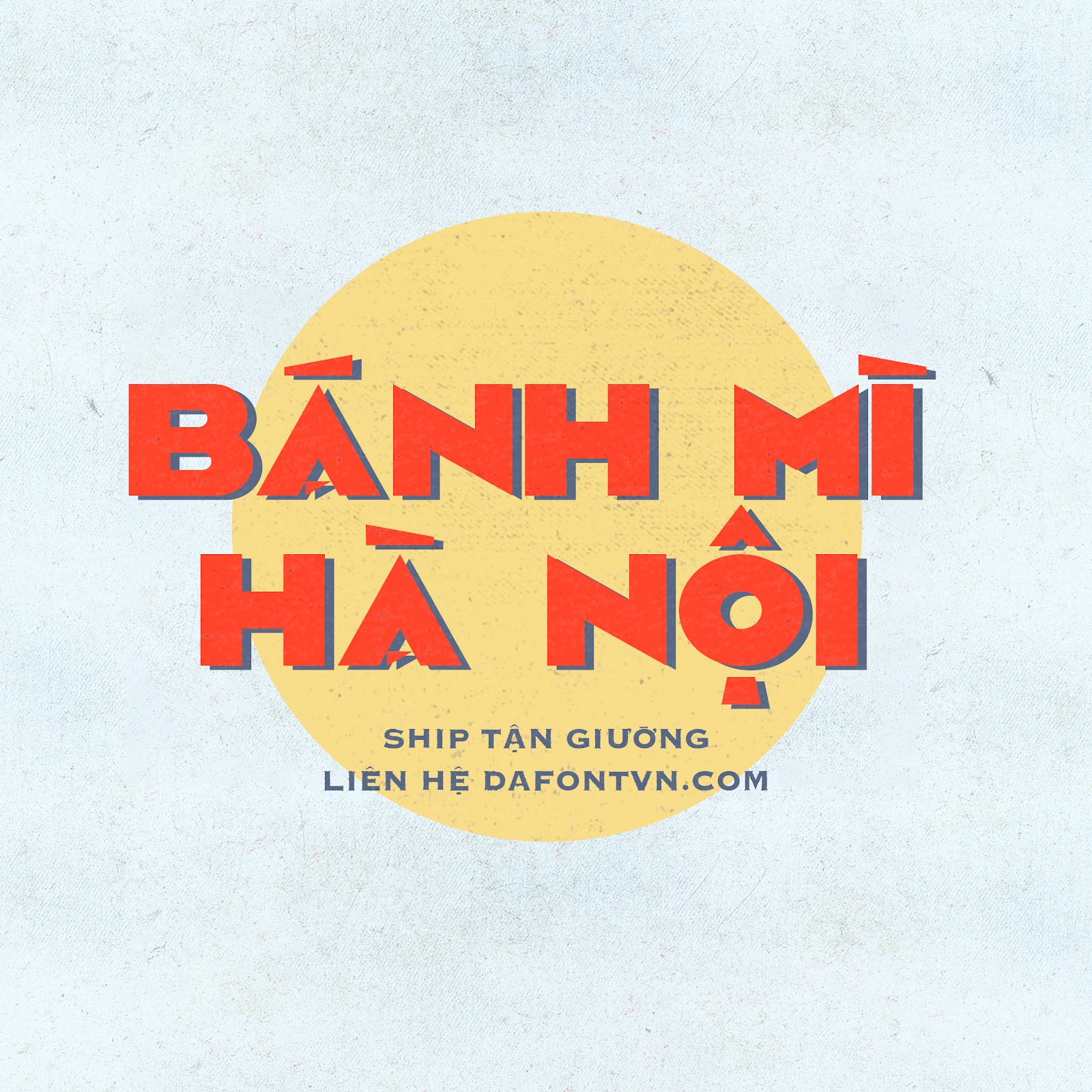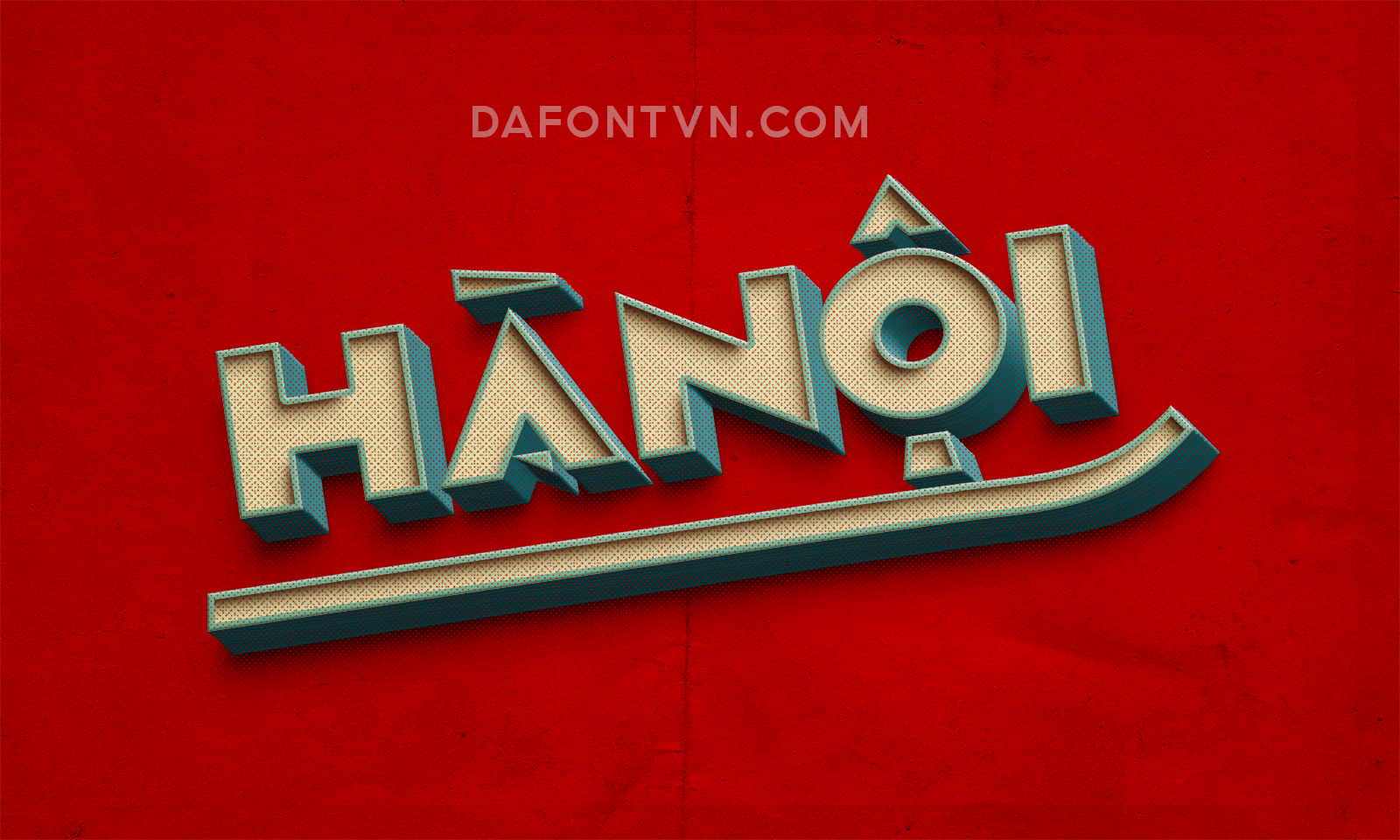
Camar Font – Đây là một kiểu font chữ vintage lấy cảm hứng từ những biển hiệu thời xưa mình đã việt hóa font với các dấu theo phong cách xưa cũ. Với kiểu chữ cứng cáp mang một chút cổ điển này rất phù hợp để sử dụng cho rất nhiều các thiết kế khác nhau như tiêu đề, tạp chí, biển hiệu, quảng cáo…